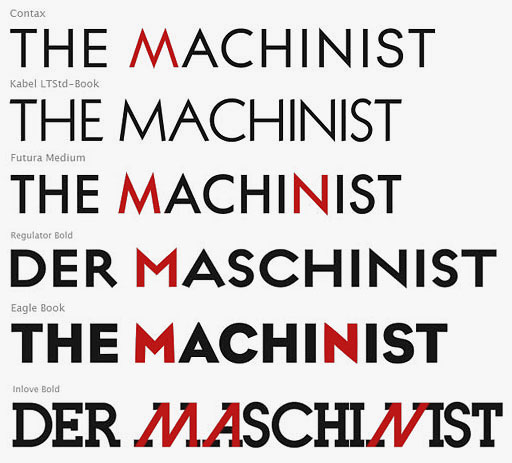
Harte Grotesk (›The Machinist‹)
ich suche eine strenge Grotesk, die dem Film The Machinist (2004) entspricht. Sie soll in erster Linie im Schriftzug zum Einsatz kommen, und dort wahrscheinlich (!) in fetten/mittelfetten Versalien.
Bisher kommt im Film Fullers Bank Gothic zum Einsatz. Ich will etwas anderes finden, eine Schrift die der kühlen, fast schon sterilen Stimmung des Films entspricht.
Sie sollte einen konstruierten Charakter haben. Es könnte die Verkörperung eines Maschinenarbeiters sein. Oder eine Schrift, die auf eine maschinelle Erzeugung hindeutet, ohne zu sehr einen OCR-Charakter zu haben.
Ich gebe zu, ich weiß schon so ziemlich, was ich will bzw. vor allem nicht will.
Zu kantige Buchstaben erinnern schnell an Football-Shirts.
Zu konstruierte Formen haben schnell einen Avant-Garde-Fashion-Charakter.
Auch Assoziationen mit "Computer" und "Science Fiction" sollten nicht aufkommen.
Ich mag die spitzen Formen einer Futura (wie auch bei den anderen Beispielen).
Auch finde ich das Statische des letzten Beispiels sehr interessant, auch wenn das runde S etwas herausfällt und ich die Schrift lieber nicht im Slab-Schnitt hätte.
FF DIN und die ganzen Monospaced-Schnitte sind sooo dumm nun auch nicht...
Ich lasse mich aber gerne auch auf "neue Wege" leiten!
Momentan favorisiere ich sowieso die "biedere" FF Bau und sein rundes Geschwisterchen Founders Grotesk.
Auch einen Blick wert ist Orbitron:
Zu modern? Nicht Neuzeit Grotesk genug?
Oder so?
Oder doch die abgegriffenen Schablonenschriften? Vinca Stencil:
Ansonsten betrachte ich die Schriften nach DIN 1451 durchaus als angemessen für das Thema.
Die Engschrift im Versalsatz (leicht gesperrt wen es geht) hat wirklich das besondere Etwas!
Ach, es ist eine Krux. Man hat halt immer den Anspruch, die perfekte Schriftart zu finden. Dabei sind die in der engeren Auswahl sicherlich alle gut genug.
Ich bin euch allen dankbar für den massiven Input, aber ich habe den leisen Verdacht dass mich das nur noch unschlüssiger gemacht hat. Doch condensed? Doch eckiger?
Momentan sind Galaxie Polaris, Flama und Founders Grotesk Favoriten. Aber gerade habe ich auch die Konsens entdeckt...
Ich denke ich sollte die Schrift schleunigst in ihren Kontext d.h. auf bewegtes Bild setzen.